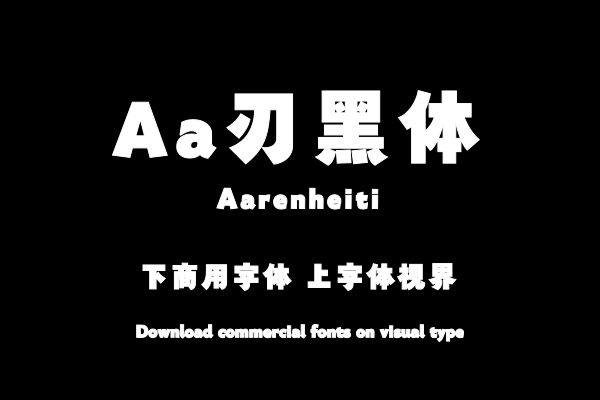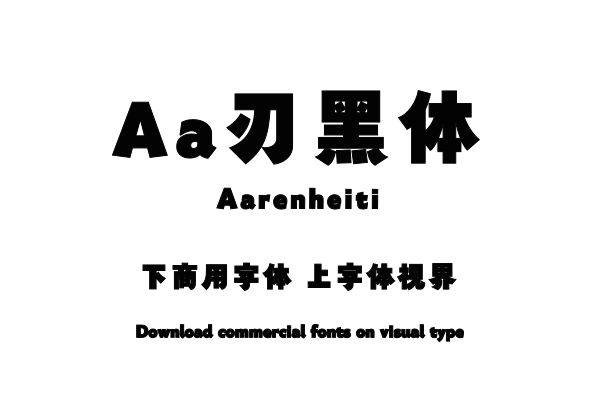
通过夸张地将一些笔画伸展外放来制作一款创意黑体。将撇捺夸张伸展如锋刃形状,提高重心缩小中宫,形成一款峻峭有力的创意黑体。购买须知:“下载服务费”与“字体VIP”所获得字体 仅用于个人非商用, 商用请联系付费授权。本字体为电脑用字,手机没有root权限不支持直接手机换字(手机如何root,请自行百度搜索教程)。购买前请先 了解清楚后再付款 ,字体为虚拟产品无法回收 一旦购买不支持退款。